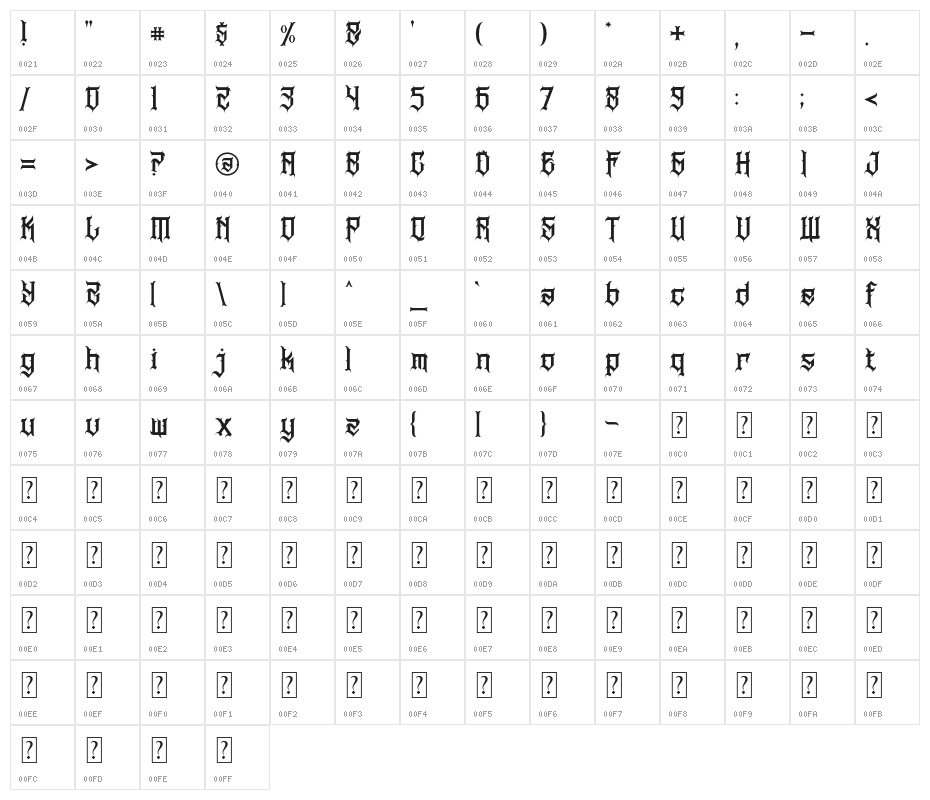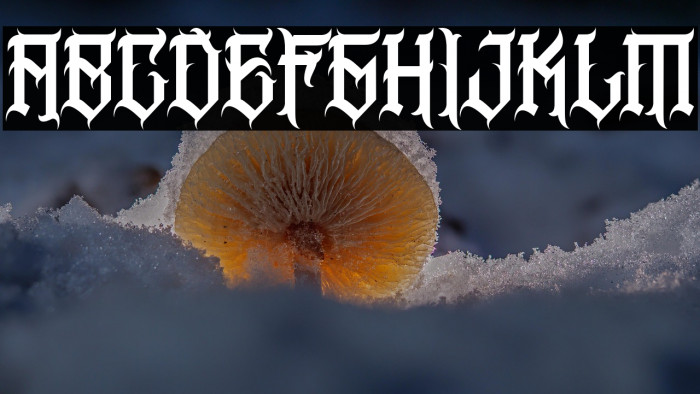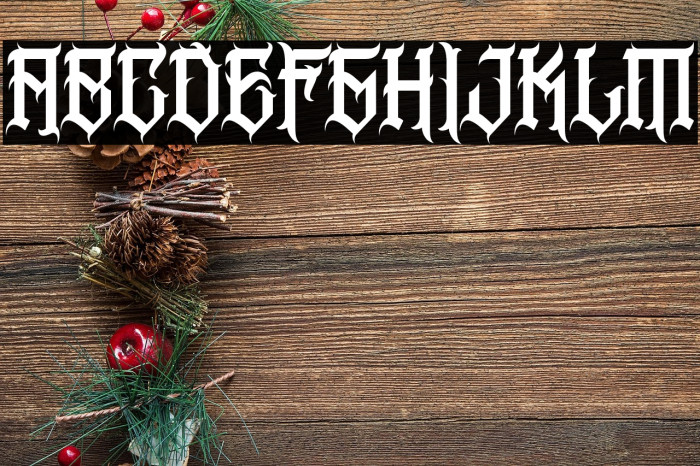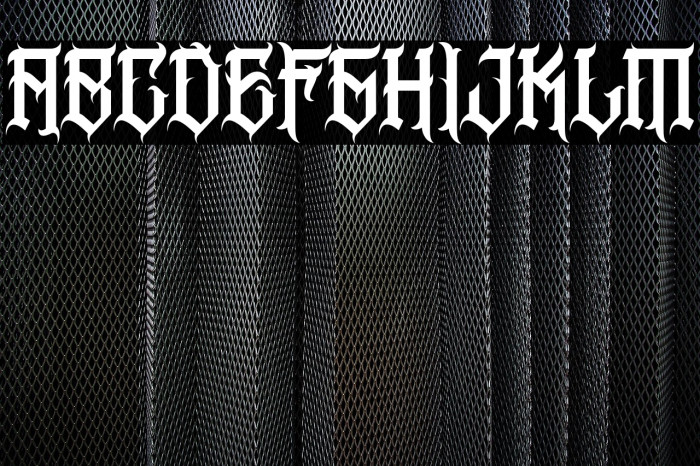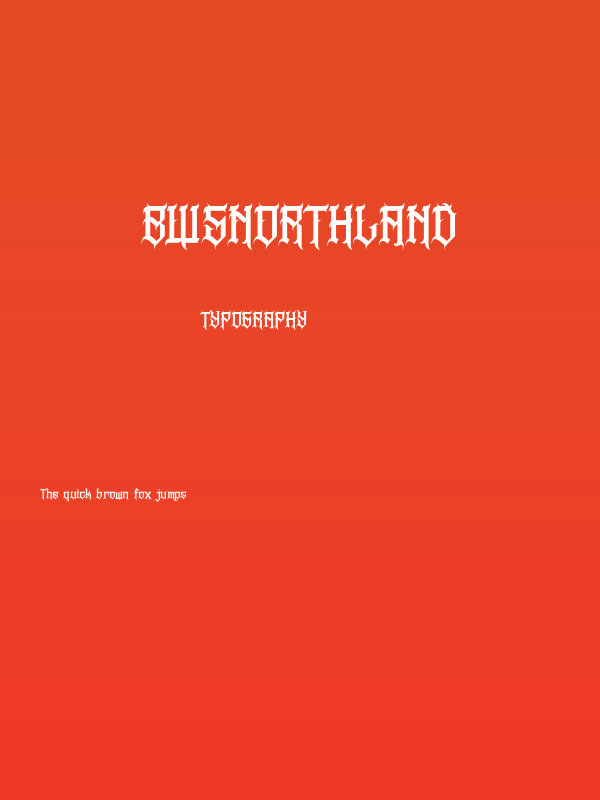
BWSNORTHLAND Font
✎ Gothic
| Projets proposés | Ideal for projects requiring a historical or gothic aesthetic, such as book covers, posters, or branding for themed events. |